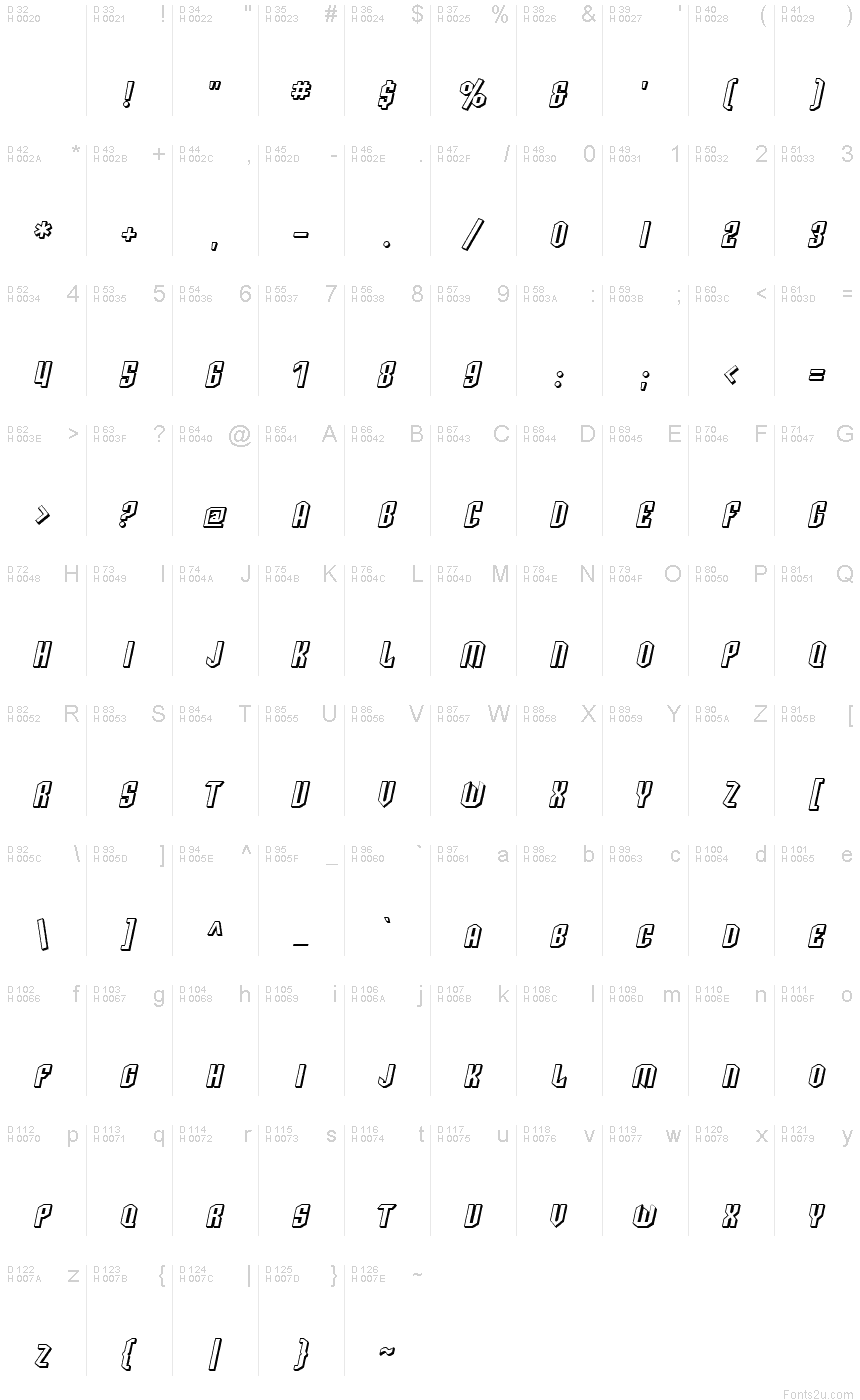
SF Archery Black SC Shaded Oblique
SF Archery Black SC Shaded Oblique, di ShyFoundry, è un font gratuito in stile techno, inclinato e tutto maiuscolo, con la grinta di un poster sportivo. Le lettere si inclinano in avanti con forme a blocchi spesse, angoli smussati e una pesante ombra che dona al carattere un aspetto tridimensionale e scolpito, invece del solito look futuristico liscio.
È perfetto per loghi di giochi, branding sportivo, titoli di poster, copertine di fumetti e cartelli, dove aggiunge movimento senza perdere la sua silhouette imponente. Grazie alle maiuscole ampie, angolari e alla profondità integrata, si adatta bene anche a monogrammi e titoli brevi che richiedono uno stile rapido e d'impatto.